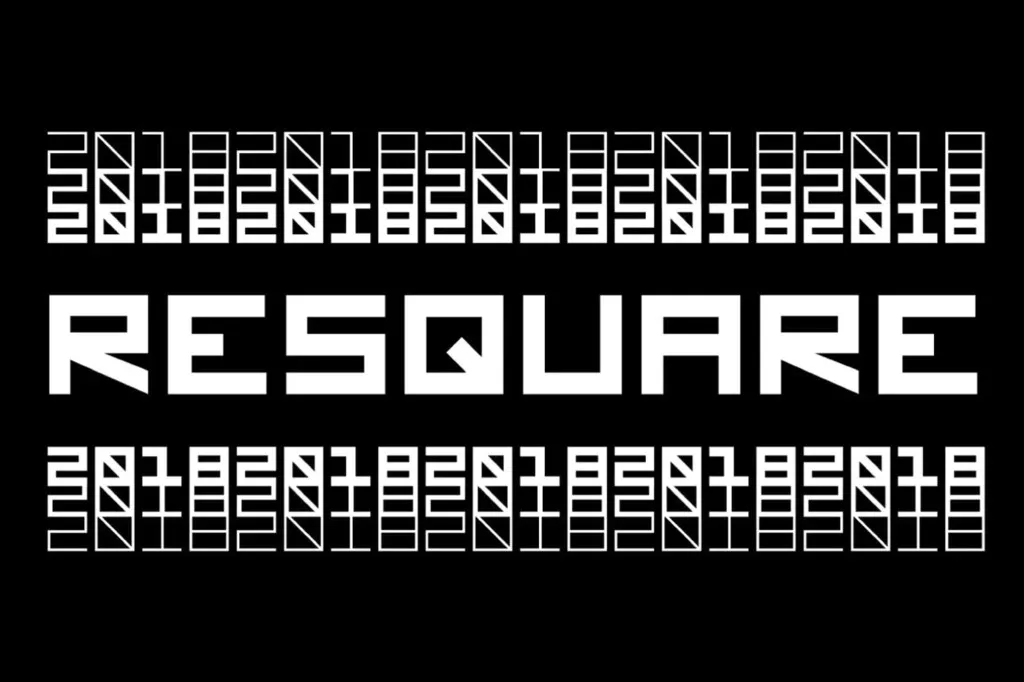
A fonte Resquare é perfeita para quem busca estilos modernos e elegantes, ideal para usar nas seções de headlines, logotipos e até mesmo na criação de cartões de visita e materiais impressos. Ela foi desenvolvida por Tikhon Reztcov no formato de tipo display, oferecendo 3 diferentes pesos: Regular, Medium e Bold. Resquare é uma escolha ótima para projetos visuais variados como roupas, merchandising e produtos impressos em geral. É uma opção versátil que certamente encantará os criativos do design gráfico. Com seu estilo único, a fonte Resquare tem se destacado na categoria de tipo display oferecida por 99designs, um local onde designers e clientes encontram e compartilham ideias para projetos visuais inovadores.